Font chữ thời bao cấp đang được nhiều thương hiệu F&B, thời trang và thiết kế sáng tạo tại Việt Nam ưa chuộng trở lại. Ở bài viết này, In Viva tổng hợp các font mang phong cách hoài cổ đáng tải nhất, kèm hướng dẫn ứng dụng và những sai lầm phổ biến cần tránh khi dùng nhóm font này.
Dưới đây là các font mang phong cách bao cấp và retro Việt hóa được dùng phổ biến nhất trong thiết kế hiện nay, kèm thông tin định dạng và nguồn tải cho từng font.
Đặc điểm của font chữ thời bao cấp
Không có một định nghĩa cứng nhắc cho nhóm font này – “font thời bao cấp” dùng để chỉ các font mang đặc trưng thẩm mỹ của giai đoạn 1975 – 1986 tại Việt Nam và phong trào đồ họa retro Đông Âu xã hội chủ nghĩa cùng thời kỳ.
Bốn đặc điểm nhận dạng chung của nhóm font này:
- Nét chữ thô, đều, ít tương phản: do hạn chế kỹ thuật in ấn thời kỳ đó, chữ thường có nét dày đều, không có sự khác biệt rõ giữa nét đậm và nét nhẹ như serif hiện đại.
- Dáng chữ condensed hoặc block: cần nhồi nhiều thông tin vào không gian hạn chế trên băng rôn và áp phích, khiến chữ thường được kéo hẹp hoặc thiết kế dạng khối đặc.
- Serif slab hoặc sans-serif hình học: hai kiểu phổ biến nhất trong ấn phẩm tuyên truyền và bao bì hàng hóa thời kỳ này, cả hai đều tạo cảm giác chắc chắn và uy quyền.
- Cảm giác thủ công, không hoàn hảo: khác với font kỹ thuật số hiện đại được làm phẳng hoàn toàn, font retro bao cấp thường có các chi tiết hơi lệch, gợi lên cảm giác in tay hoặc in ty-pô.
Ứng dụng của font chữ thời bao cấp trong thiết kế
Phong cách bao cấp hoạt động hiệu quả nhất khi toàn bộ hệ thống thiết kế — font, màu sắc, texture và bố cục — cùng hướng về một thẩm mỹ thống nhất, không chỉ đơn thuần thay font.
- Thương hiệu F&B và cà phê phong cách retro: bao bì kraft, menu in một màu, nhãn chai sử dụng font slab serif thô mang lại cảm giác thủ công và chân thực mà thiết kế hiện đại khó đạt được.
- Ấn phẩm văn hóa, sách và tạp chí độc lập: Playfair Display kết hợp với bố cục nhiều cột gợi lên thẩm mỹ báo in và tạp chí thời đổi mới.
- Poster sự kiện và triển lãm nghệ thuật: font block condensed trên nền màu đơn sắc tạo ngôn ngữ thiết kế mạnh, dễ nhận dạng và có chiều sâu văn hóa.
- Thời trang và merchandise hoài niệm: áo, túi, sticker dùng font bao cấp kết hợp với màu nâu, kem, đỏ gạch và texture giấy ố tạo ra sản phẩm có tính sưu tầm cao.
Gợi ý phối font thực chiến: dùng một font block đậm như BC Lodestone cho tiêu đề, kết hợp BC Rostrum hoặc Playfair Display Regular cho nội dung phụ. Không nên trộn quá hai font retro trong cùng một thiết kế — tập trung vào một font chủ đạo và để màu sắc cùng texture làm phần còn lại.
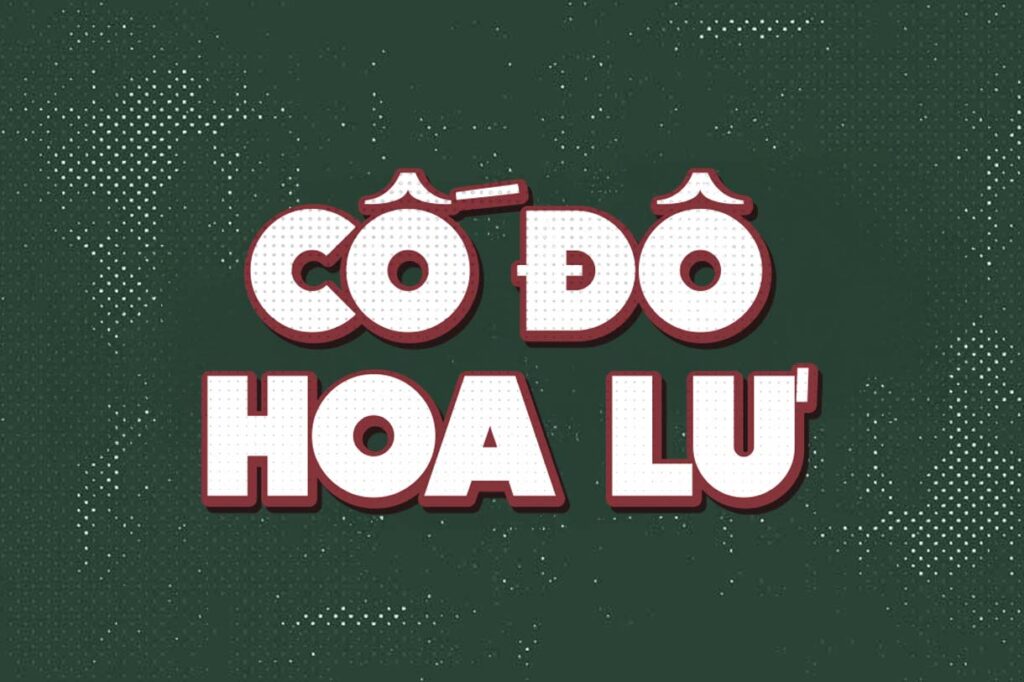
04 sai lầm thường gặp khi dùng font chữ thời bao cấp
Font hoài cổ dễ bị lạm dụng hoặc dùng sai bối cảnh, khiến thiết kế trông lỗi thời thay vì có chủ đích retro. Bốn sai lầm dưới đây xuất hiện thường xuyên nhất.
- Dùng font bao cấp trên nền trắng sạch không có texture. Font retro đặt trên nền trắng phẳng của phần mềm trông như font cũ chưa được thay, không tạo ra cảm giác hoài cổ có chủ đích. Cần thêm overlay texture giấy ố vàng, grain film hoặc nền màu đất để font phát huy đúng phong cách.
- Phối màu sai thời kỳ. Dùng màu neon, gradient tím hồng hoặc bảng màu pastel hiện đại với font bao cấp tạo ra sự mâu thuẫn thẩm mỹ rõ ràng. Tông màu gốc của thời kỳ này là nâu đất, kem ngà, đỏ gạch, xanh quân sự và đen, giữ đúng bảng màu này để thiết kế nhất quán.
- Trộn quá nhiều font retro trong một thiết kế. Mỗi font bao cấp đều có cá tính mạnh. Dùng 3 – 4 font retro cùng lúc tạo ra sự hỗn loạn thay vì cảm giác thời kỳ. Giới hạn tối đa 2 font, trong đó một font làm vai trò tiêu đề và một font làm nội dung phụ.
- Dùng font TCVN3 cổ mà không kiểm tra bản quyền. VnTime và nhiều font TCVN3 được chia sẻ rộng rãi trực tuyến nhưng nguồn gốc bản quyền không rõ ràng. Với dự án thương mại, nên dùng font có giấy phép rõ ràng như Playfair Display trên Google Fonts hoặc mua bản SVN Việt hóa có giấy phép đầy đủ.
Font bao cấp phù hợp nhất với chất liệu in nào?
Giấy kraft tự nhiên, bìa carton chưa tráng phủ hoặc giấy xi măng. Các chất liệu này tạo nền màu ấm, kết hợp với font retro cho ra cảm giác thủ công và hoài cổ tự nhiên hơn in trên giấy couche trắng bóng.